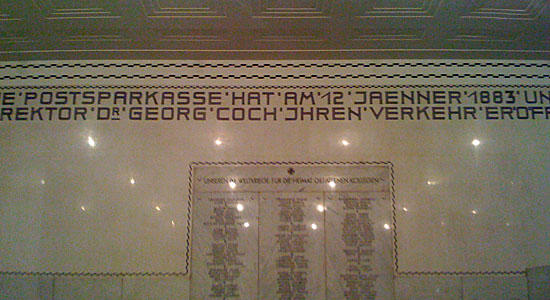
Schrift in der Wiener Postsparkasse von Otto Wagner
Sieht schwer nach Wiener Werkstätten aus. Mein Büchlein darüber ibt leider nichts her.
Bist du sicher das dieses (schöne) Lettering auf eine Bleisatzschrift zurückgeht, ich meine 1 zu 1?
Beim Herrn Bleisetzer im Forum oder in Person von Mike Janega (Yanega?) auf typophile.com gibt's vielleicht mehr Infos …
Wie toll – ist das eine Kachelmosaikschrift? :biglove:
Scheint (in gröber und abstrahiert – hier ist noch eine Ecke) dem typographischen Vorbild der Außenbeschriftung (original, aktuell) zu folgen; die hat ähnliche, wenn auch elegantere Proportionen und natürlich mehr Details. Das typographische (beschriftungsmäßige?) Grundkonzept scheinen die Leute heute immer noch mehr oder minder zu befolgen. Spannend.
.. und der Otto hat sich sogar eine TT-Ligatur gebaut (anderer Winkel) :D
Will sagen: Ich würde mich wundern, wenn es die Innenbeschriftung als Satzschrift gäbe. Für mich sieht das wirklich aus wie eine medienspezifisch angepasste Variante der Außenbeschriftung – welche schon sehr viel mehr wie eine «gewohnte» Jugendstilschrift wirkt.
Wenn ich könnte, würde ich … aber ich mach jetzt die Industria. :wink:
Dank für eure Hinweise. Ich denke auch, dass es sich um eine
spezielle Schrift für dieses Haus handelt oder zumindest um
die Abwandlung einer typischen Schrift der Zeit. Deshalb ja auch
gleich am Anfang schon die Frage nach ähnlichen Schriften.
Ich werd mal weitersuchen und euch auf dem laufenden halten!
im newsletter von myfonts kam gerade die "bala cynwyd" von nick curtis reingeflattert.
vielleicht findest du bei ihm ja was, er hat viel so art deko zeugs. der mitropa-font geht
auch etwas in die richtung, weil kantig und so. aber genau sowas wirst du wohl kaum finden.
Hat immerhin gewisse Ansätze?